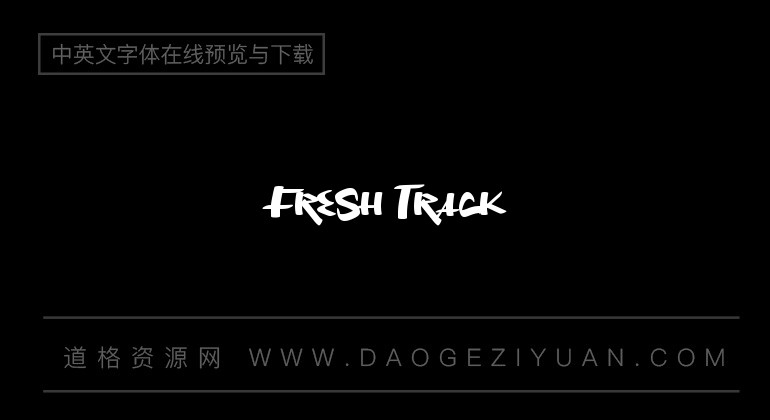
Fresh Track 是一种现代风格的英文字体,于2020年由设计师 Fenix Azure 倾力打造。该字体以新鲜和活力为特色,适用于许多设计项目,如海报、标志、包装、书籍、杂志、网站等。 Fresh Track 字体包括 Regular 和 Italic 两种样式,每种样式都包括大写字母、小写字母、数字和标点符号。该字体的设计具有高度的可读性和可识别性,同时保持了现代感和独特性。它的线条流畅,轮廓清晰,适合使用在大标题和短语上。 Fresh Track 字体的许可证允许在个人和商业项目中免费使用,但不允许再分发和出售。它提供了多种格式,包括 TrueType、OpenType 和 Web 字体,可以方便地在各种设计软件和网页中使用。内容介绍
Fresh Track是一款非常不错的手写艺术字体,具有很好的视觉感,适合于文化类的宣传设计、商业类品牌的广告和产品包装设计以及个性化文字排版等较多场景。